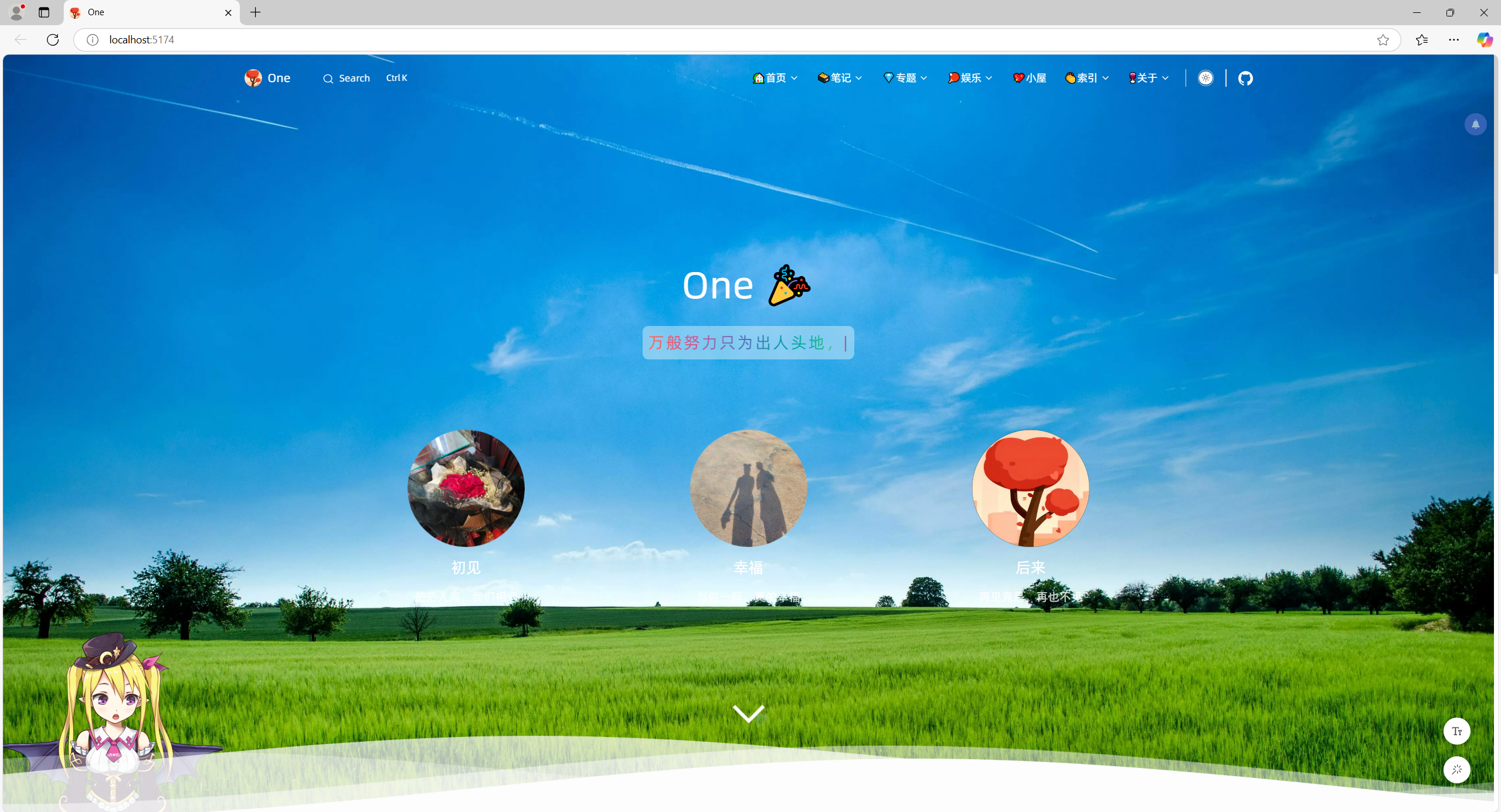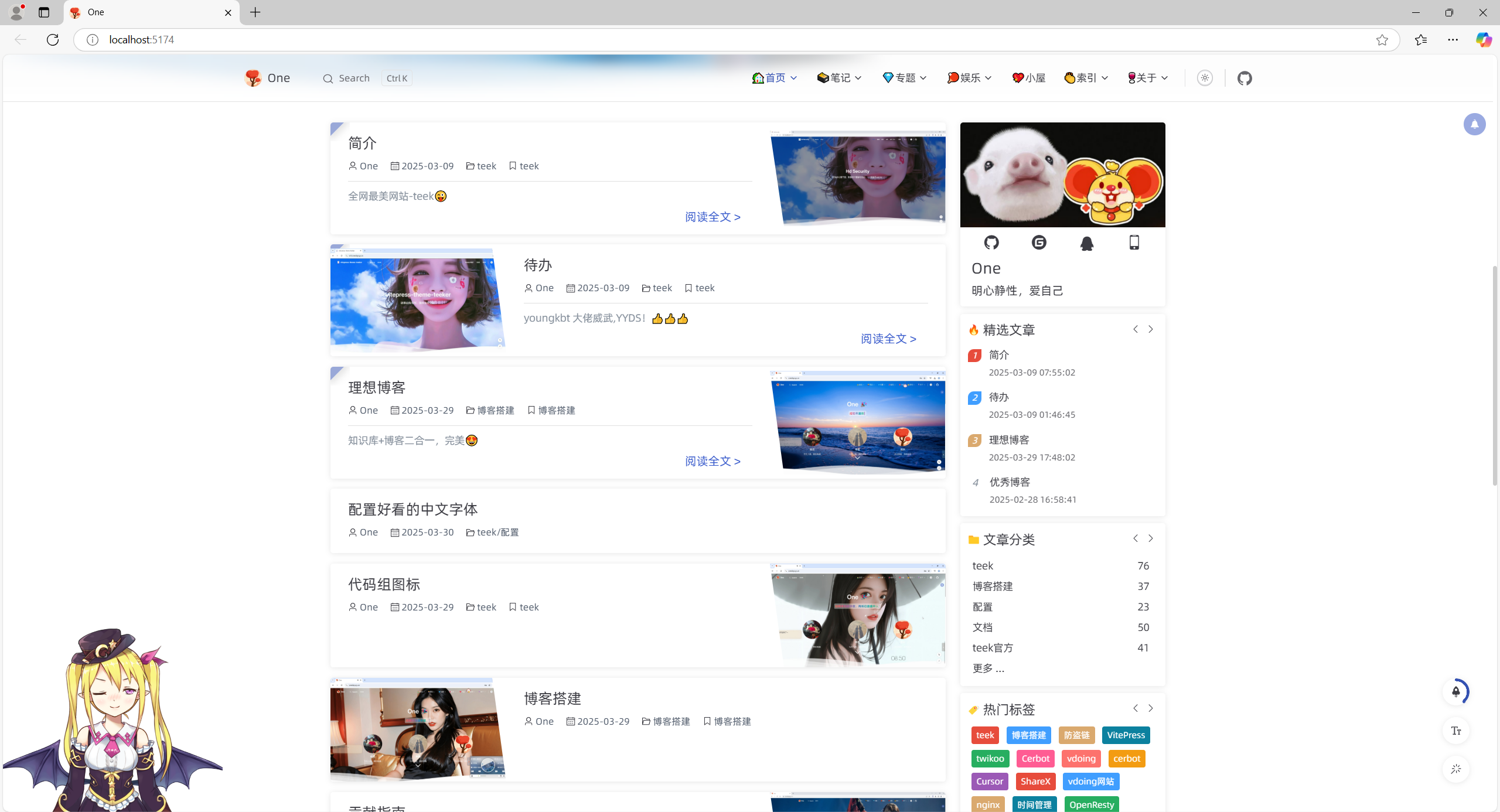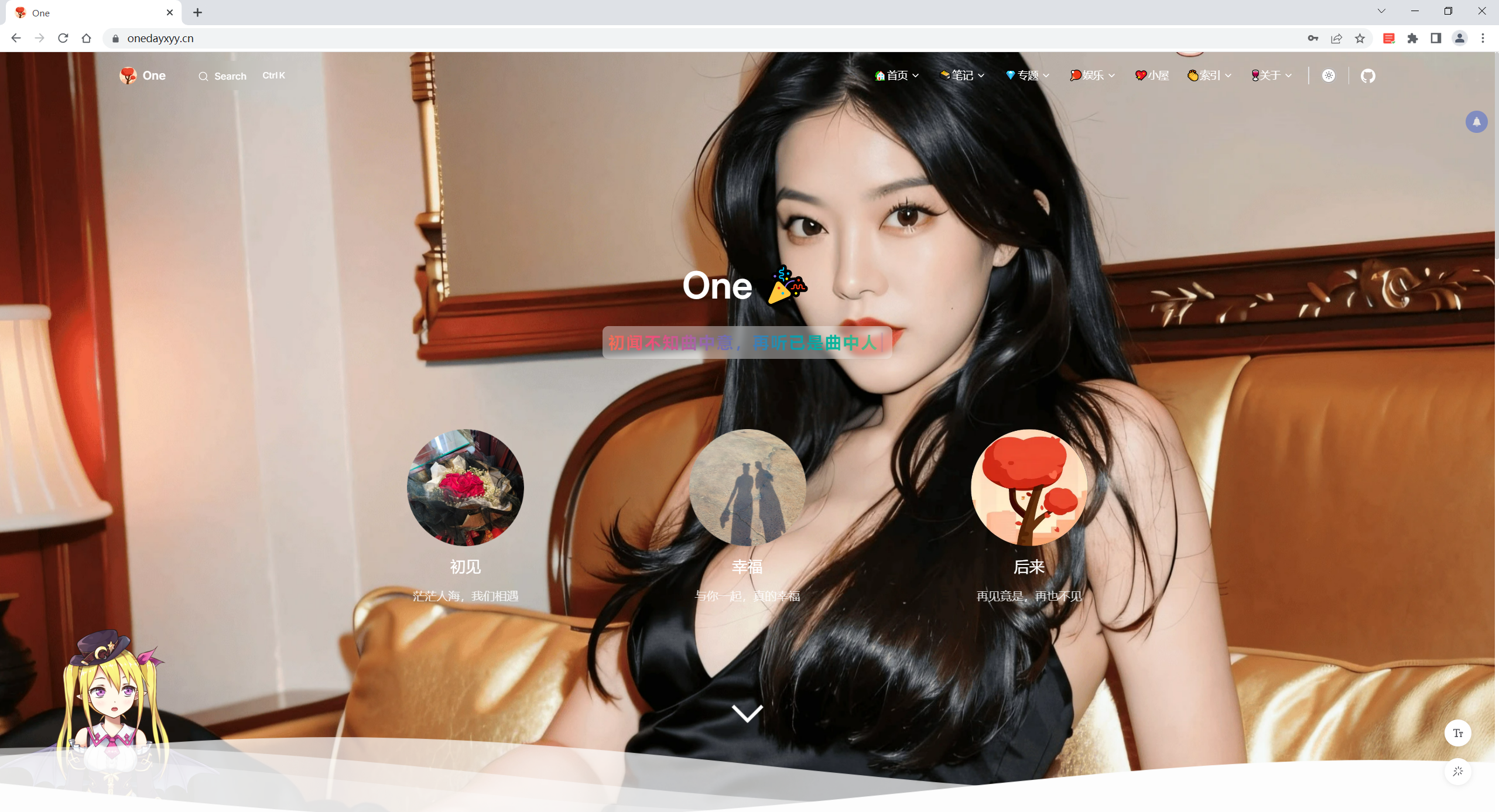
配置好看的中文字体
给自己博客配置一个好看的中文字体吧……
前言
给自己博客配置一个好看的中文字体吧……
效果
image-20250329205522189
image-20250329205542299
配置
(3)运行,验证效果
更新
自己最后选择了筑紫A丸作为自己网站字体。(这个字体的确很好看哦,强烈推荐)。配置内容和上文一样。
扩展
优化字体加载方式